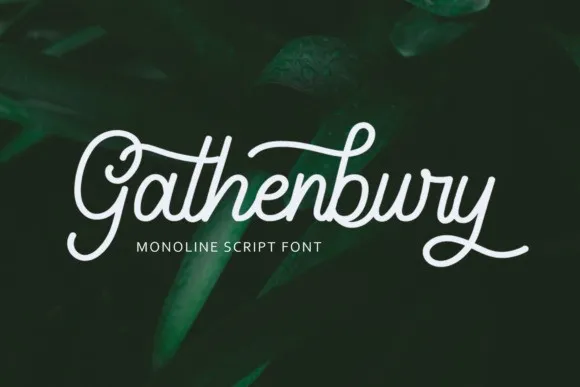
Gathenbury Script Font
Seja um amante do bom design ou um entusiasta da escrita, Gathenbury Script é uma fonte script que combina a elegância dos caracteres antigos com a modernidade de formas contemporâneas. Ideal para quem busca algo diferente e criativo no seu próximo projeto gráfico, esta fonte é perfeitamente adaptada para o uso em logotipos, capas de livros, embalagens, menus de restaurantes, cartões de convite e anúncios. Gathenbury Script traz um toque serio e sofisticado à sua arte digitais, permitindo-lhe incorporar uma autenticidade única em seus projetos. Construída a partir do mix entre a pontilhada tradicional e as linhas modernas de tipo, Gathenbury Script é perfeita para aquelas criações que precisam de um toque especial. Este novo repositório Typeface Fonts da agamous oferece uma combinação única de clássico e atualidade, proporcionando um contraste interessante que se assemelha ao estilo autêntico do Gathenbury Script. É perfeitamente adequada para ambientes onde o design deve comunicar em termos sutis e elegantes, como capas de livros ou cartões de convite para eventos especiais. Seja você um designer gráfico iniciante ou experiente, Gathenbury Script oferece uma escolha interessante no seu repositório de fontes. Com um toque autêntico que combina clareza com sofisticação, esta fonte é a escolha perfeita para quem busca um novo elemento na sua paleta de fontes.